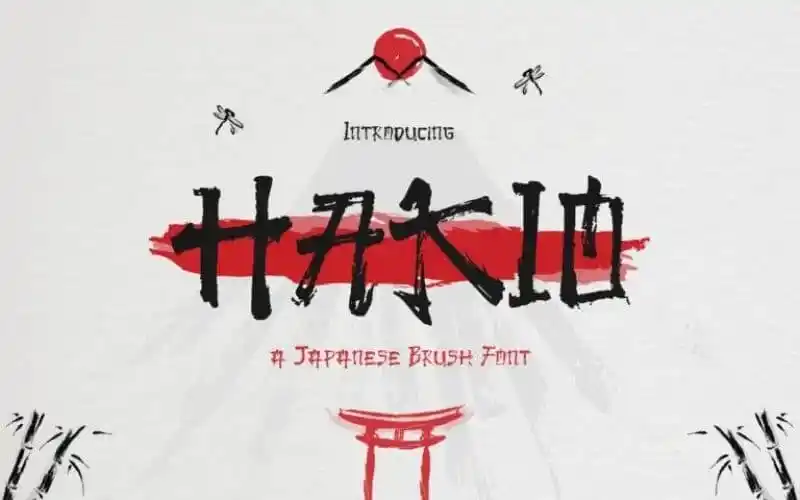
Hakio Brush Font
A Hakio Brush Font é uma tipografia de letra a mão, cuidadosamente desenhada para transmitir a rica história do Japão — sua paixão, tradição e arte. Ideal para criações que valorizam a delicadeza e a autenticidade dos estilos japoneses tradicionais, esta fonte foi criada pelos arquitetos de design 99designs em parceria com os amantes da cultura japonesa. Suas linhas suaves e fluidas lembram obras de arte, transmitindo ao mesmo tempo um sentimento autêntico e um toque moderno. Seja para revistas de design, artigos de design ou qualquer projeto que exige uma fonte com alegria vibrante e sutileza, Hakio Brush Font é o ideal escolha.